原研哉の品牌字型美学
Kenya Hara
原研哉の品牌字型
—
字体是品牌形象重要的组成部分,也是品牌传播日常中不可缺少的元素,究竟字体对品牌有何效用,如何为品牌设计字体?本期特以原研哉的经典案例来作一些分享,从中感受品牌
字型气质的重要性。通过案例剖析经典品牌背后的字体故事。
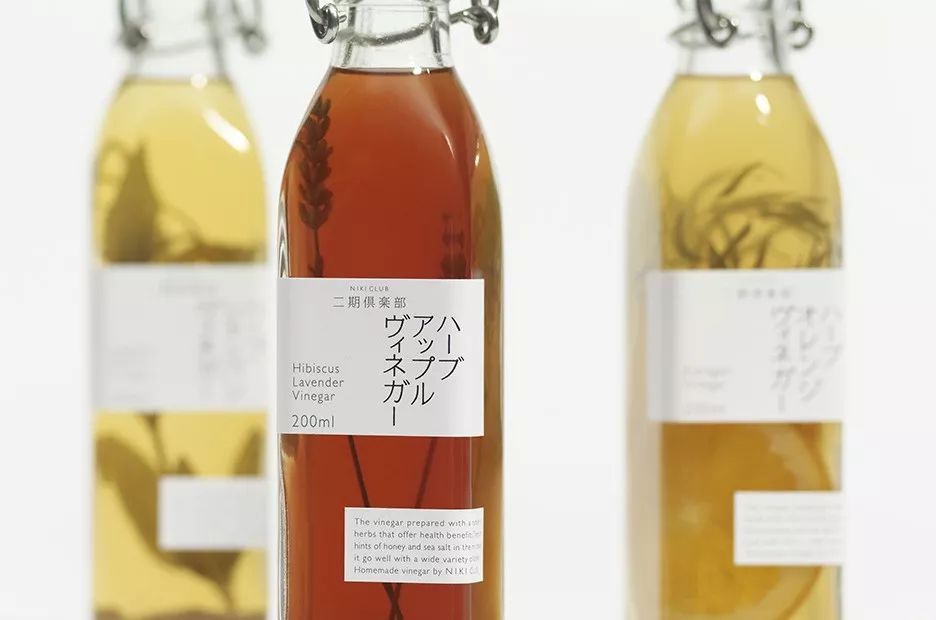
Niki Club
「二期俱樂部」视觉形象
设计诠释
—
Niki Club新形象从接待服务的质量与精心营造的空间、以及广阔的自然景观,这些都是二期俱乐部的重要资产。为了进一步提升自身的品牌形象,迈向下一阶段的发展,NDC对
Niki Club进行了"二期字体"的设计与开发,并以此设计作为新Logo的字型。
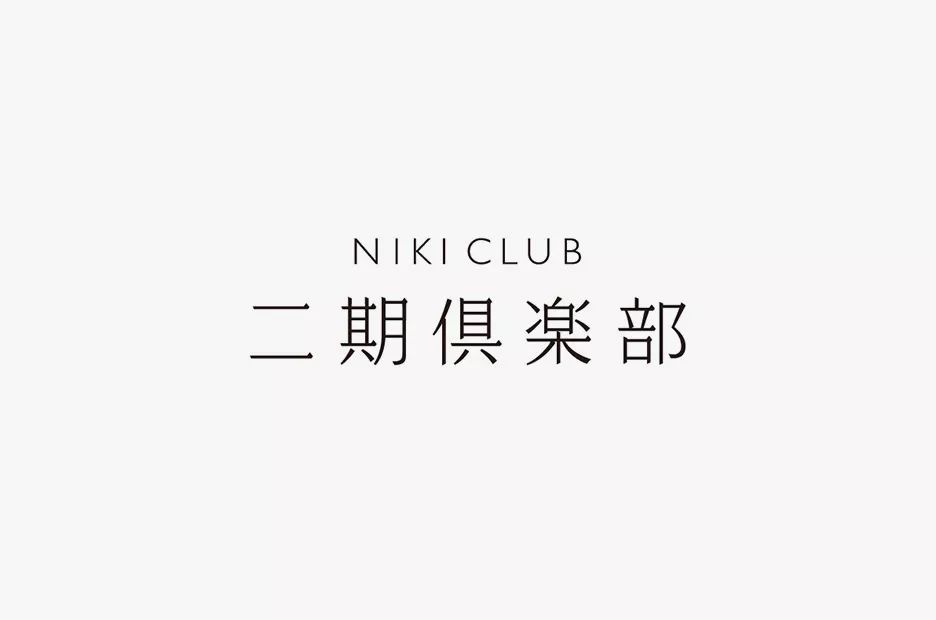
字体的设计理念
—
新的字型虽然看上去笔划略细,但内部却坚而有力、仅仅只是展示文字亦能显得有张力且美观。这就是NDC重塑Niki Club新形象的设计理念。在所有的物料及包装的应用上
我们都能感受到这种新字型所带来的美感。
整体字型纵横笔画的粗细均衡,笔画间的等线、切脚、几何化曲线等特征与西文匹配,字面宽度则取自字母「N」的字宽,进行等幅设计。整体字形高阔、明朗,重心平稳,
在与富于节奏变化的西文组版中求以安静,满足观众获取流畅的信息。
在保留基础风格的同时,字风清秀明快,即现代又不失时尚感,在设计界赢得广泛好赞。
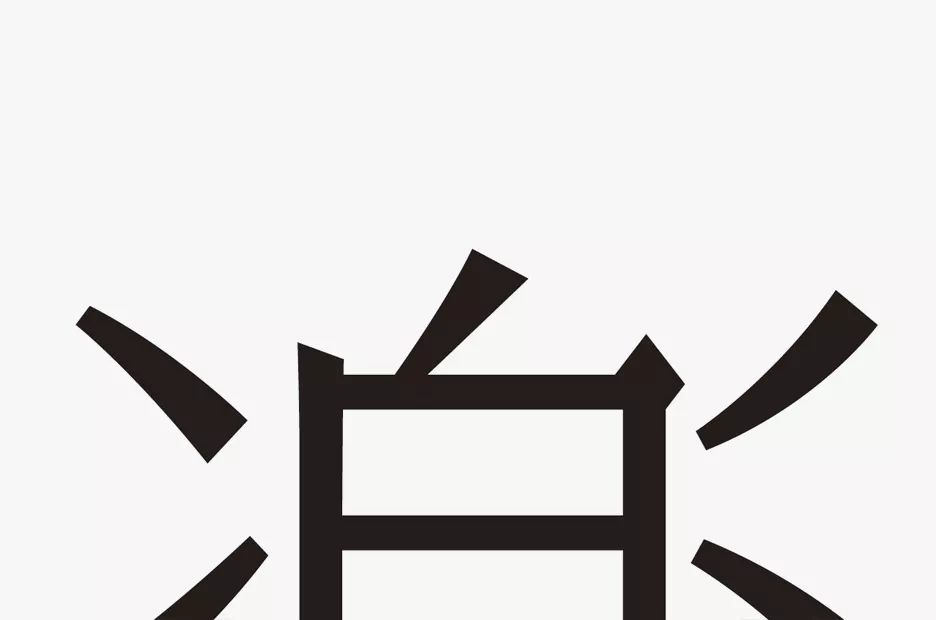
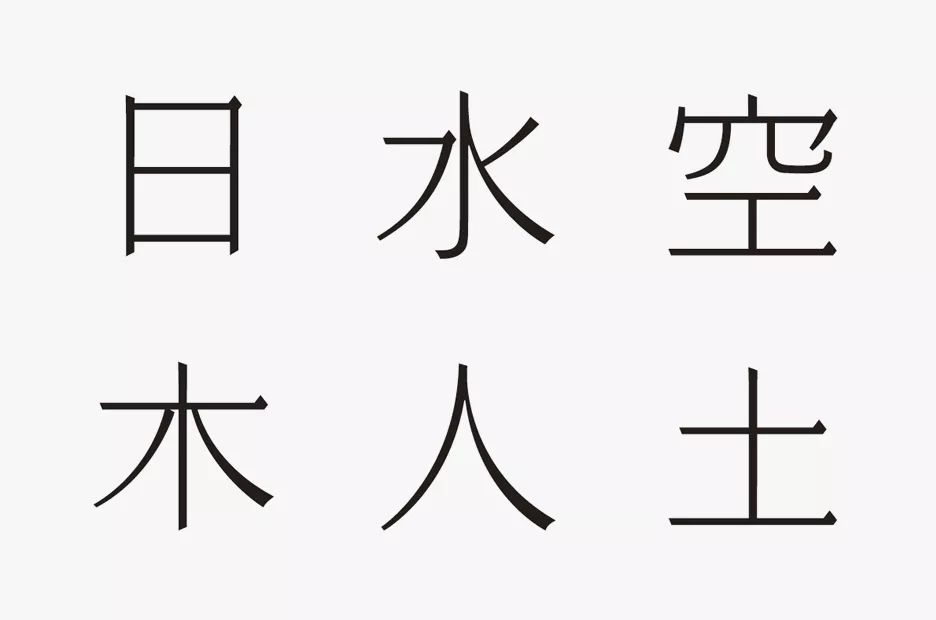
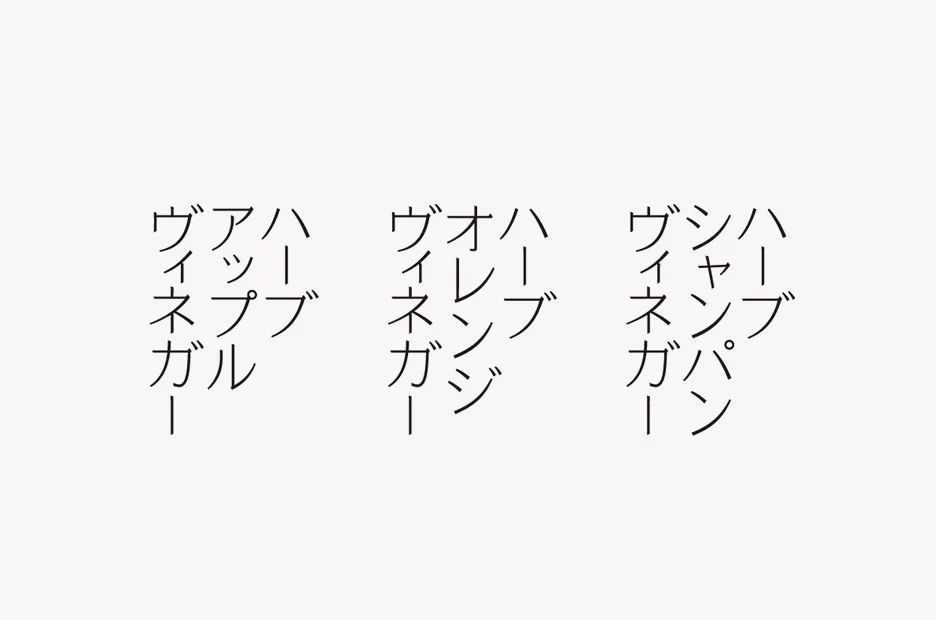
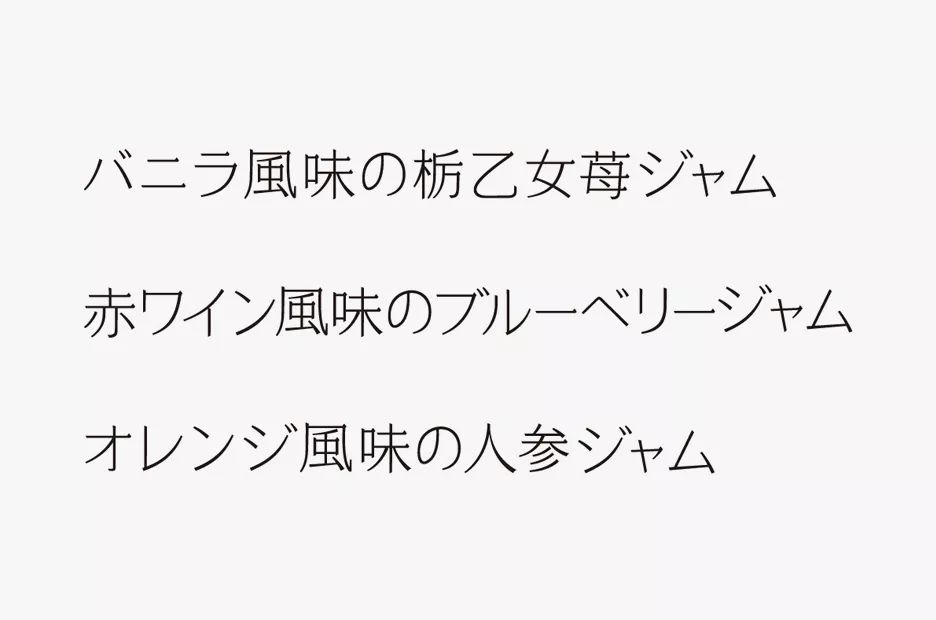
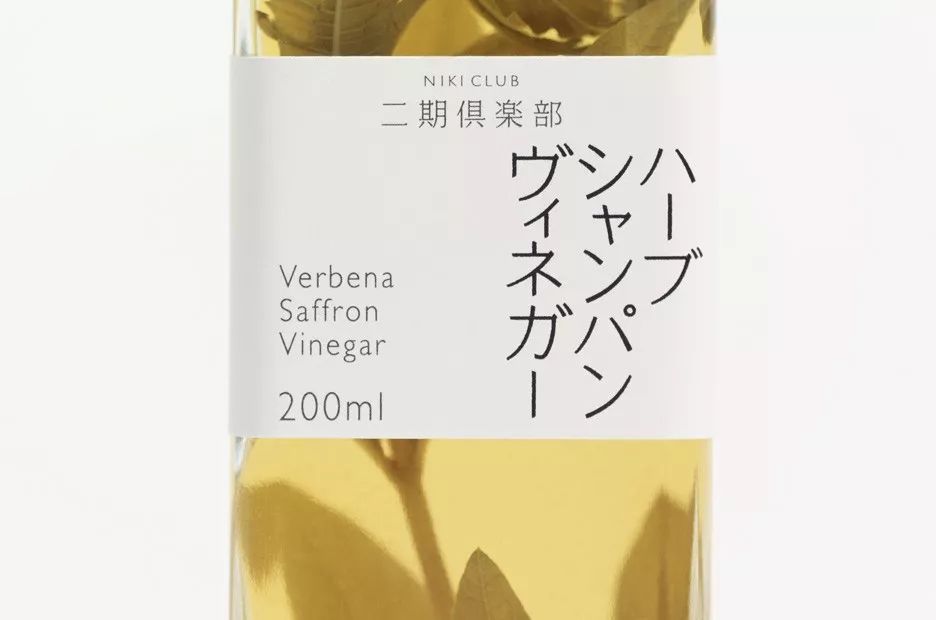
化繁为简、更显优雅
—
对于原创产品,采用的是摒弃一切多余的装饰,直接由文字和留白构成的包装设计。这不仅仅只是精心地对文字进行编排组合,
更是一种文字美感驾驭力的彰显。
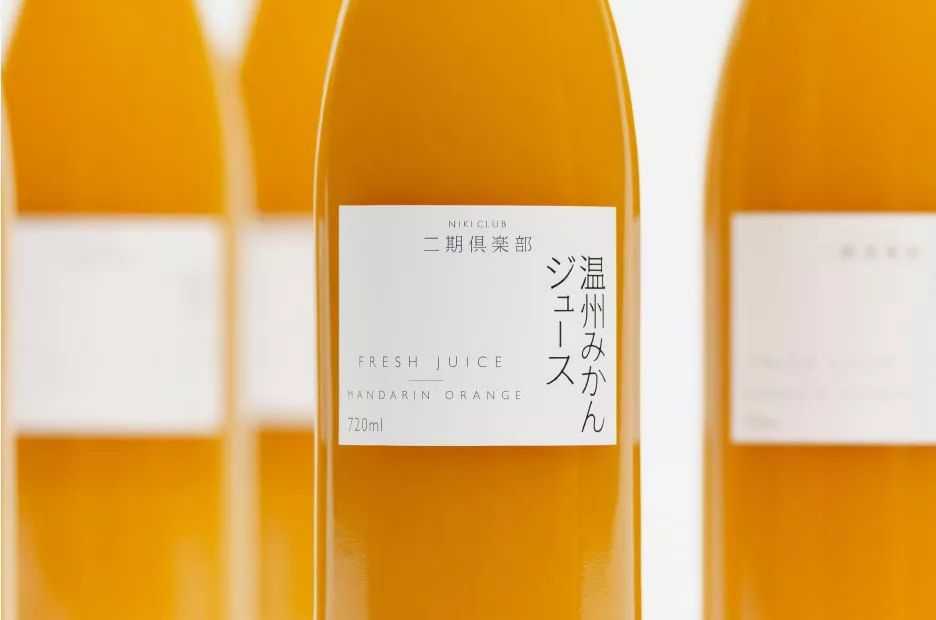
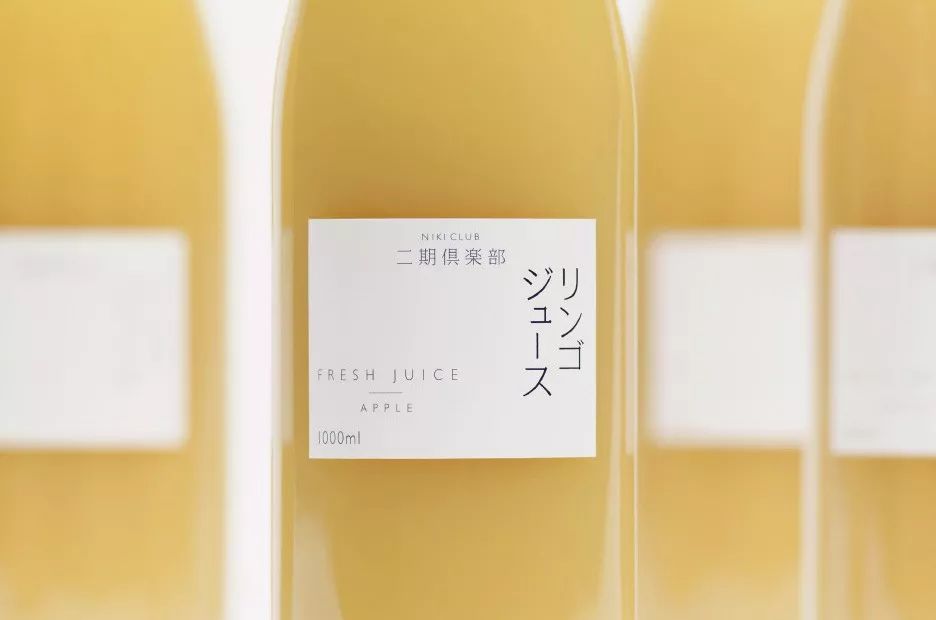
TEASURE
煮葉
煮葉 TEASURE"是一个以“设计现代人的日常”为理念,结合中国传统茶饮的方式。打造的一个具有浓厚东方文化底蕴的现代茶饮体验空间。原研哉负责了整个品牌形象的LOGO
设计、VI和包装,还有空间设计和茶具设计、以及佐茶食品的指导工作。
字体的东方意蕴
—
煮葉TEASURE品牌标志LOGO设计以中文“煮葉”两字为设计元素,字体延续了Niki Club的字型风格。采用繁体字的设计形式,相对于简体汉字而言,视觉上会更加的平衡与和谐。
设计带有传统与现代结合的方式中英文的组合,字体都是经过精心设计提炼而成。
充满着东方意蕴的简约之美,给人简约、自然、质朴的美学印象。除作LOGO字型应用外,还开发了一些品牌专属字样以适合用来标记茶叶的品种 ,
应用在后期的茶叶包装上。让整个品牌形象看上去更加系统。
专属的客制字体设计,针对不同茶叶的品种及种类。
—
漂浮的茶叶
—
清柔淡雅的茶叶包装设计。使用的字体是与LOGO相同的字型,
与漂浮在水中的茶叶相得益彰。
竹材的应用
—
店内的装饰采用了竹材,因为竹子的质感非常适合品味中国茶。竹原本是唐宋时期人们最常用的材料,而古人在制茶的过程中也会大量使用竹制品,采茶的背篓、喝茶的茶器,都
由竹制成。
在原研哉的眼中,竹既能代表东方,也跟茶有着紧密的关联。
竹与茶的东方意象,在原研哉设计的煮葉空间中体现得淋漓尽致。
Tsutaya Books
茑屋书店
茑屋书店的形象同样也应用了明朝体字型做为品牌的Logotype,简洁且明快。
Logotype
汉字与粒子元素
—
书店的Logo从“TSUTAYA”转变为“茑屋书店”,Logo形式的焕然一新正代表了项目的寓意。VI设计上,将Logo进行粒子化处理,最终变成点的集合。
通透的结构表现
—
将冲孔金属压平形成半透明式结构。将其用在标识文字较大且易于阅读的地方。不仅材质轻薄,而且具有一定的透明性,
无论从内侧还是外侧看过去,视觉识别度都很高。
与建筑遥相呼应的广告物料
—
采用与建筑正面外观相同的设计语汇,制作了Novelty Goods。以白色为基调,力图以T的凹凸形态体现一致性。
Kusamura Books
草叢
多册汇成一籍,以同一种形式连续发行的一系列图书称为"丛书"。"丛"意味着草木丛生之地。
"茑屋书店"的简化版——"草丛BOOKS",象征如丛草般茂盛的知识产物。
明朝体字型与摩损的质感
—
在整个VI及标识系统的设计上,沿用了与茑屋书店同样的明朝体字型,保留了“茑屋书店”的特色,同时采用磨损质感、瓦楞箱材料和牛皮纸,
表现更年轻粗犷却又充满生命力的“草丛”形象。
瓦楞纸板标识牌
—
标识的材料为瓦楞纸板的工艺方式。塑造出一种粗糙感,且降低了运营成本。